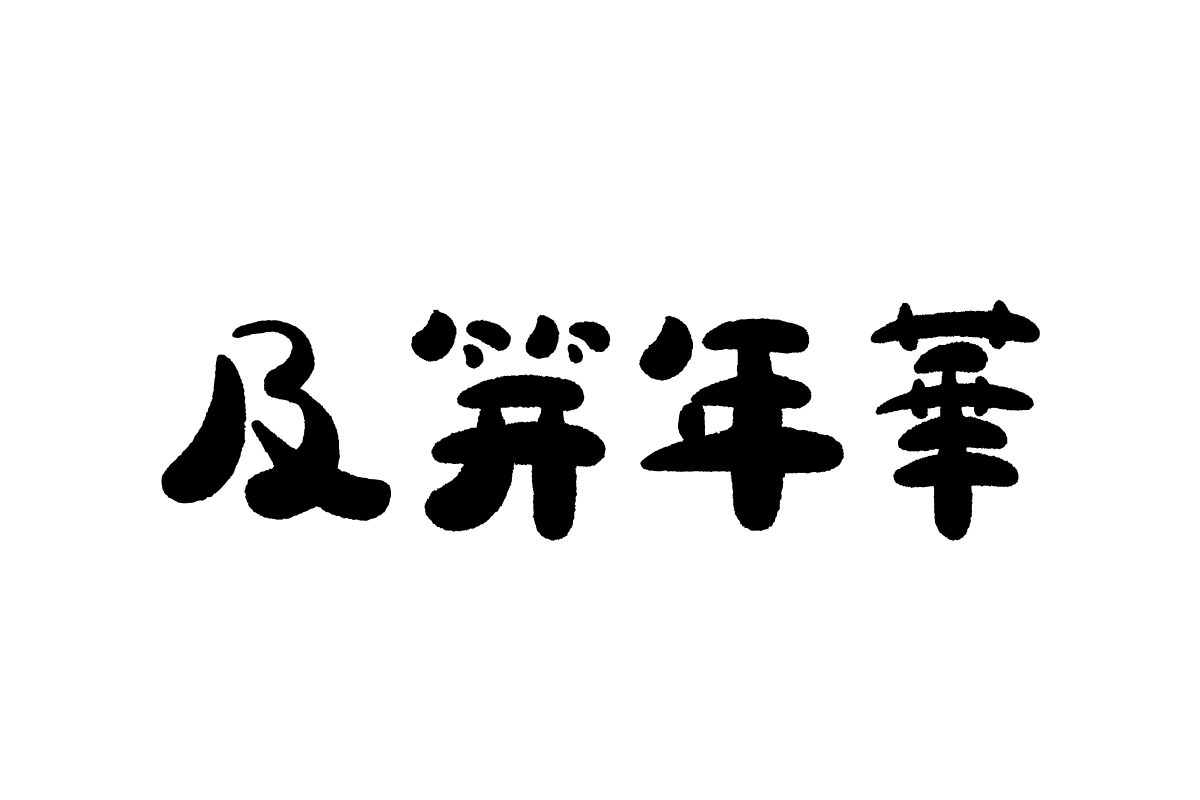
汉仪能猫体繁体是一款具有独特风格的字体,它以简洁、现代的设计语言为特点,给人一种清新脱俗的感觉。这款字体适用于各种设计场景,如广告、海报、网页等,能够很好地提升设计作品的视觉效果。
汉仪能猫体繁体的特点在于其独特的笔画形态和结构布局。它的笔画流畅自然,线条粗细适中,既符合人体工学原理,又能够展现出优雅的气质。同时,这款字体的结构布局也经过精心设计,使得整体看起来更加和谐统一。
在风格上,汉仪能猫体繁体追求简约而不简单,通过巧妙的字形变化和组合,营造出一种轻松愉悦的氛围。它既有传统书法的韵味,又不失现代感,适合用于各种创意设计。